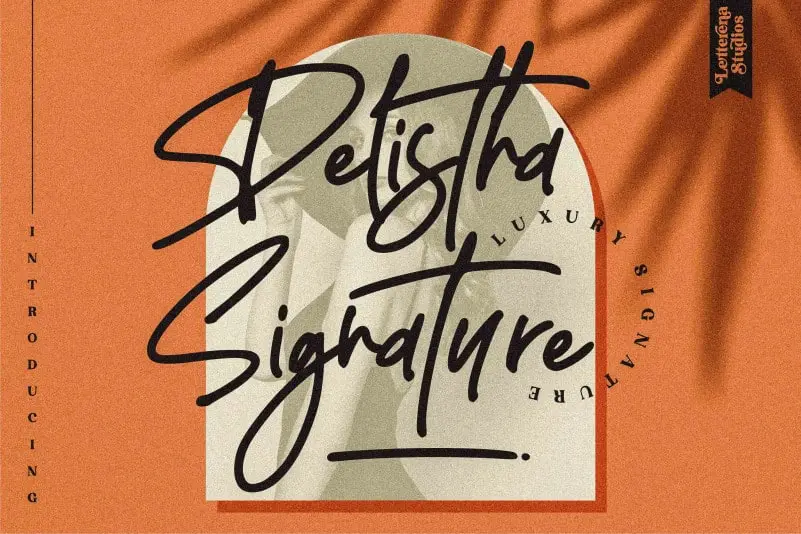
Delistha Signature Font – Download Grátis
Delistha Signature Font é uma elegante fuçna escrita a mão que se destaca por sua proporção perfeita entre espessura e finura. Suas traços são delicados o suficiente para dar um toque suave à sua obra, sem ser frágil ou opaco. Delistha foi projetada em uma variedade cíntica de linhas, garantindo que você sempre tenha a fonte perfeita para cada projeto. Seja ela um e-mail personalizado, um anúncio impresso ou até mesmo um design gráfico exclusivo, Delistha Signature Font irá enriquecer sua obra, tornando-a única e encantadora. Ideal tanto para textos de uso cotidiano quanto para títulos de página inteira, esta fuçna escrita a mão é uma escolha perfeita para designers que buscam um estilo elegante e sofisticado sem perder o toque personalizado da escrita à mão. Delistha Signature Font foi projetada pela letra nasta studios e oferece uma variedade de opções para tornar cada projeto ainda mais especial.